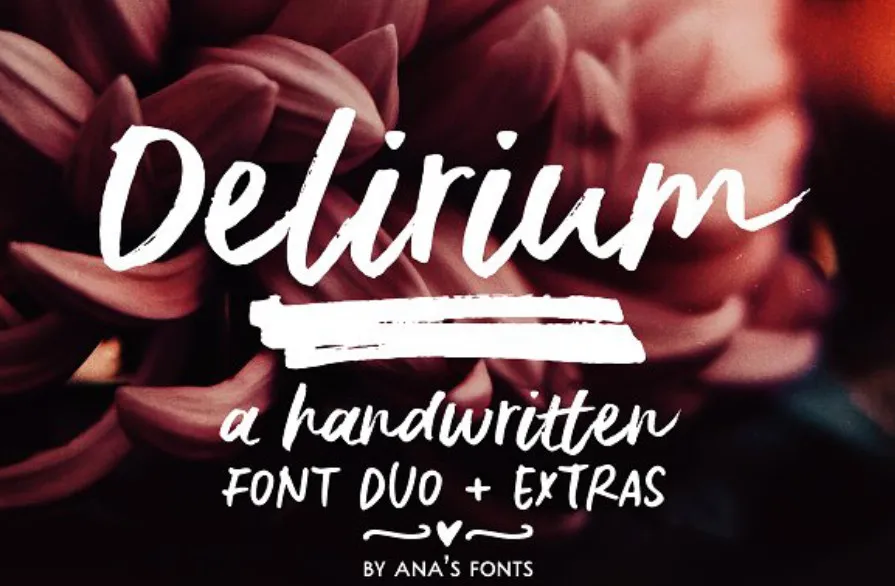
Delirium Brush Font – Fonte Grátis
Delirium Brush Font
Aqui está uma descrição para a página de download da font ‘Delirium Brush Font’, mantendo o tom informativo e convidativo: Combinando delicadeza com autenticidade, a Delirium Brush Font oferece um estilo único que combina elementos do hand-drawn com tecnologia moderna. Especificamente projetada para os designers, esta fonte brush atende diversos usos, desde logos memoráveis até cartões de aniversário e postagens no Instagram. A Delirium é uma dupla de fontes escritas a mão que se complementam perfeitamente, sendo ideais para criar designs exuberantes. Suas linhas suaves e expressivas permitem ao designer explorar criatividade sem limitações, tornando-a a escolha ideal não só para logotipos e materiais publicitários, mas também para cartões de convite, posts nas redes sociais, sites e embalagens. A Delirium Brush Font é perfeita para quem busca uma fonte brush com um toque único que ilumina qualquer design. Sua versatilidade faz dela uma escolha excelente para qualquer projeto visual que exija estilo e personalidade. Experimente a diferença de usar Delirium Brush Font e veja como seus trabalhos se destacam no mercado digital. Com o designer da Ana’s Fonts, Delirium oferece aos usuários a oportunidade de inovar suas criações com um estilo impecável. Escolha agora sua delírio visual!